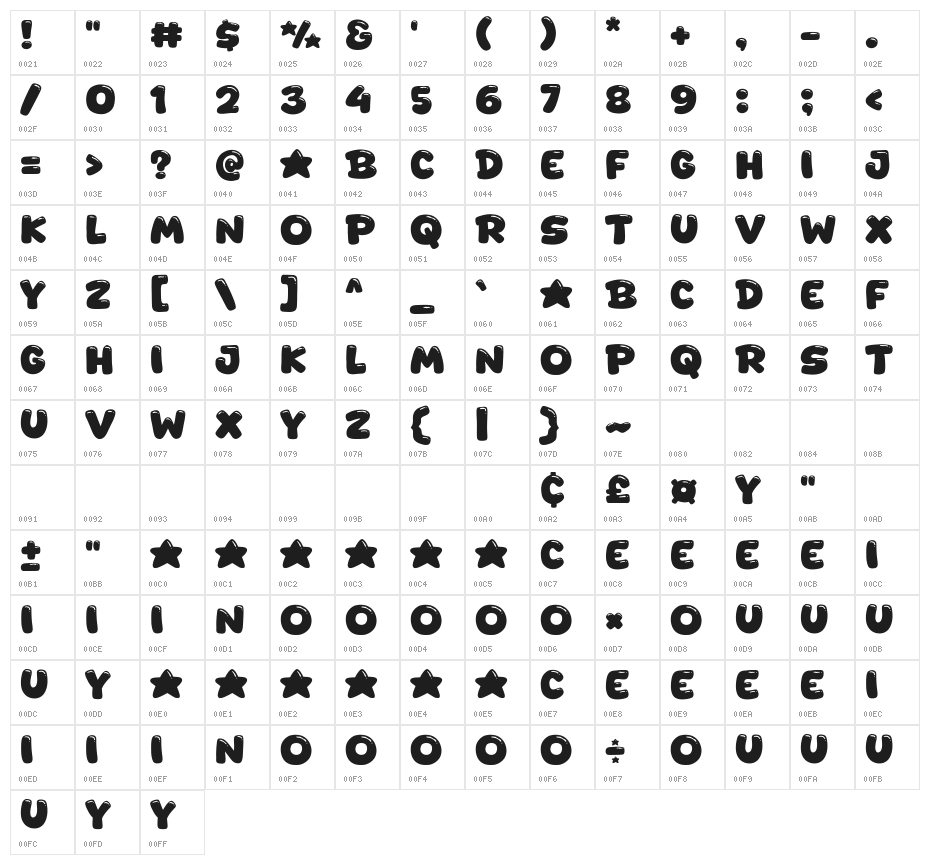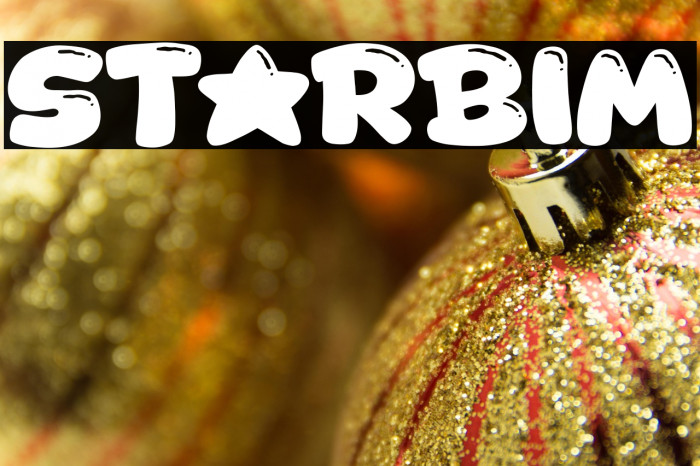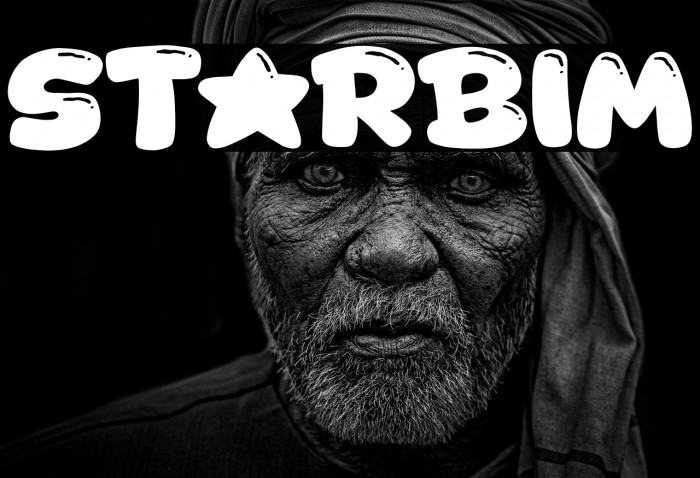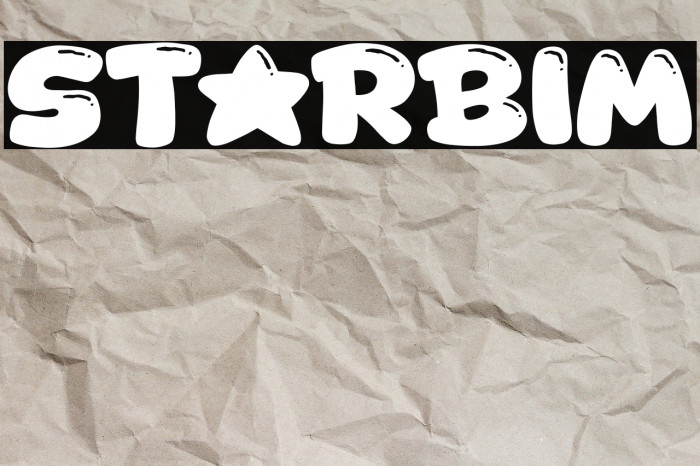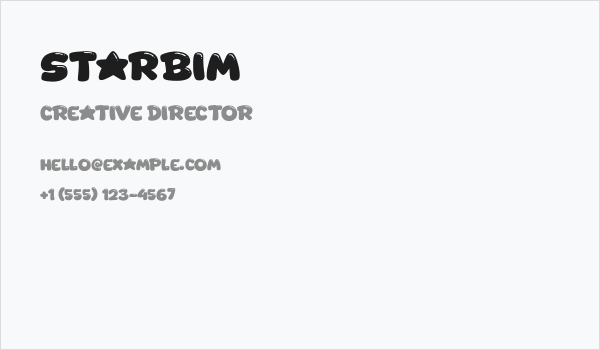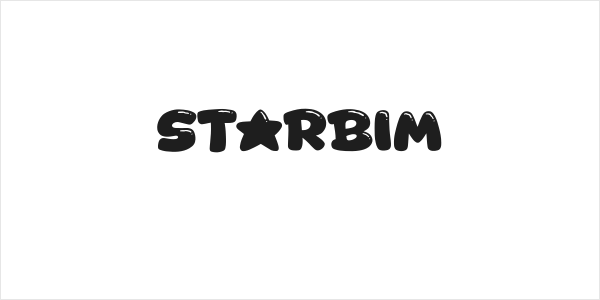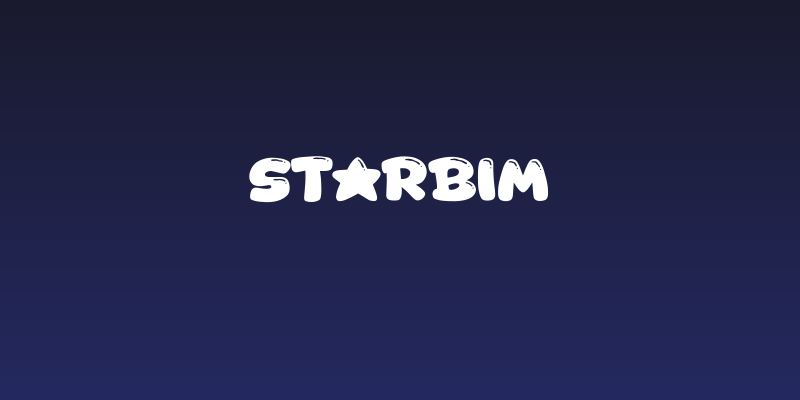
Starbim Font
| Gesamtstil | Playful, Fun, Whimsical |
| Vorgeschlagene Projekte | Ideal for children's books, playful branding, party invitations, and any project requiring a fun, eye-catching typeface. |